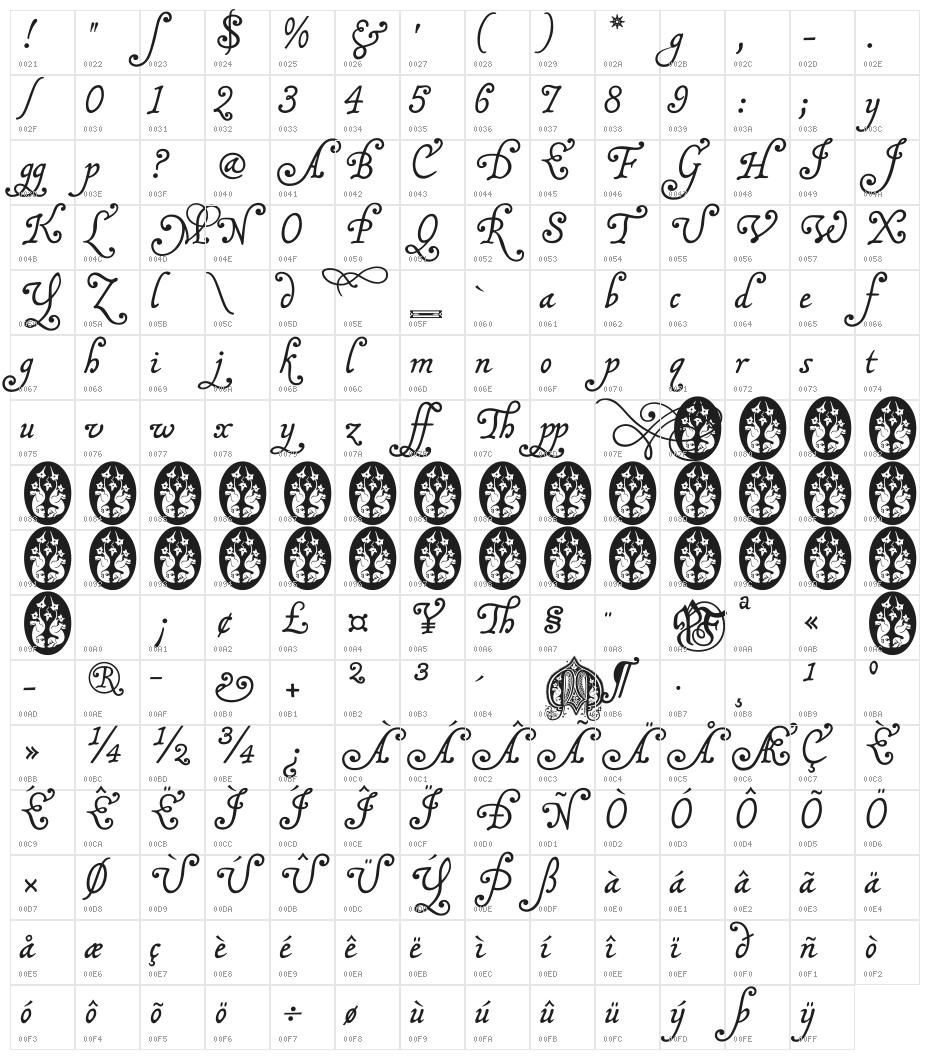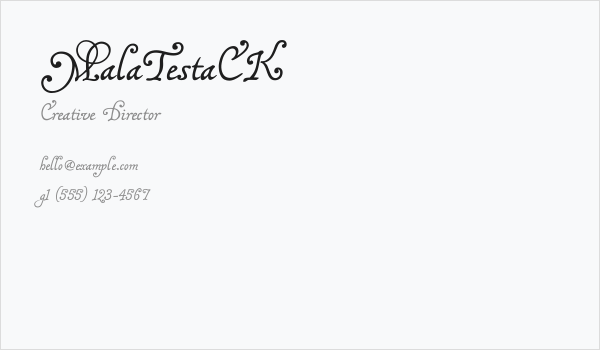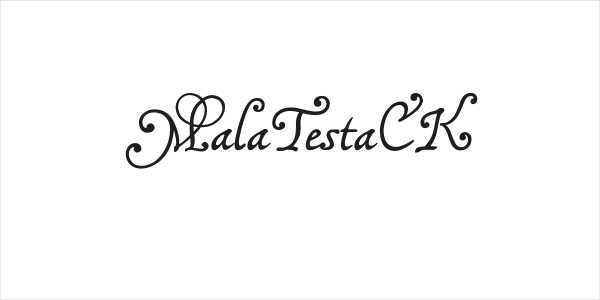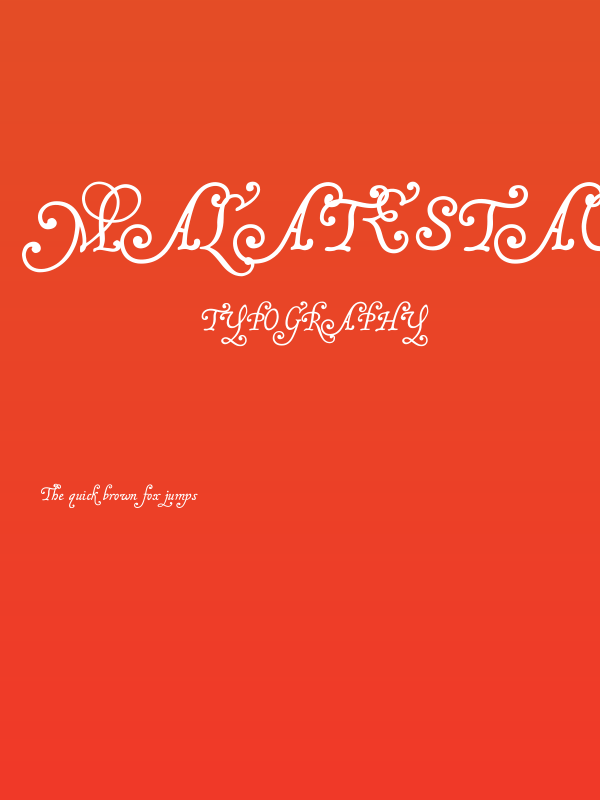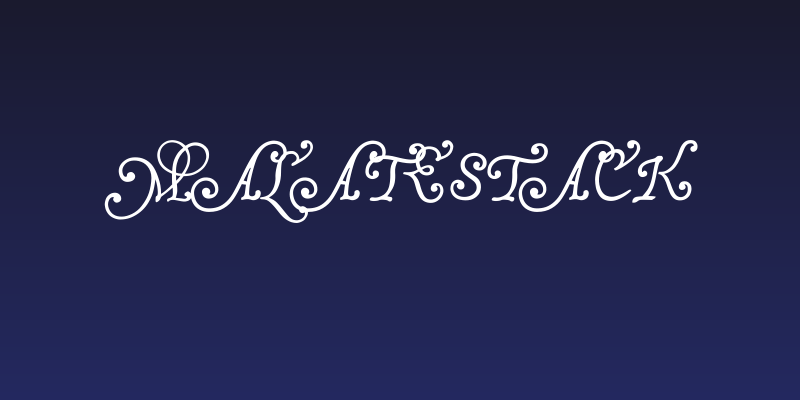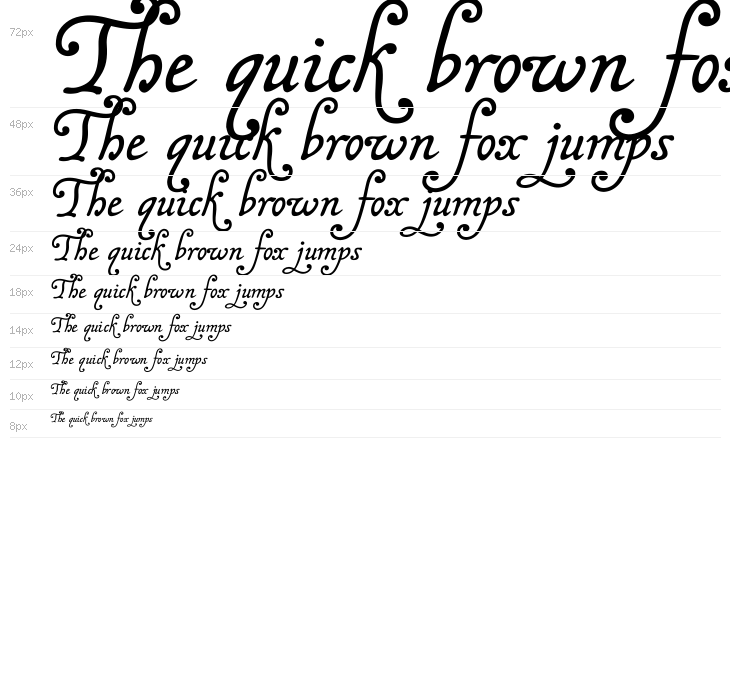
MalaTestaCK Font
| Caso d'uso | Logos, Invitations, Artistic projects |
| Progetti proposti | Ideal for wedding invitations, luxury branding, greeting cards, and artistic projects requiring a sophisticated touch. |